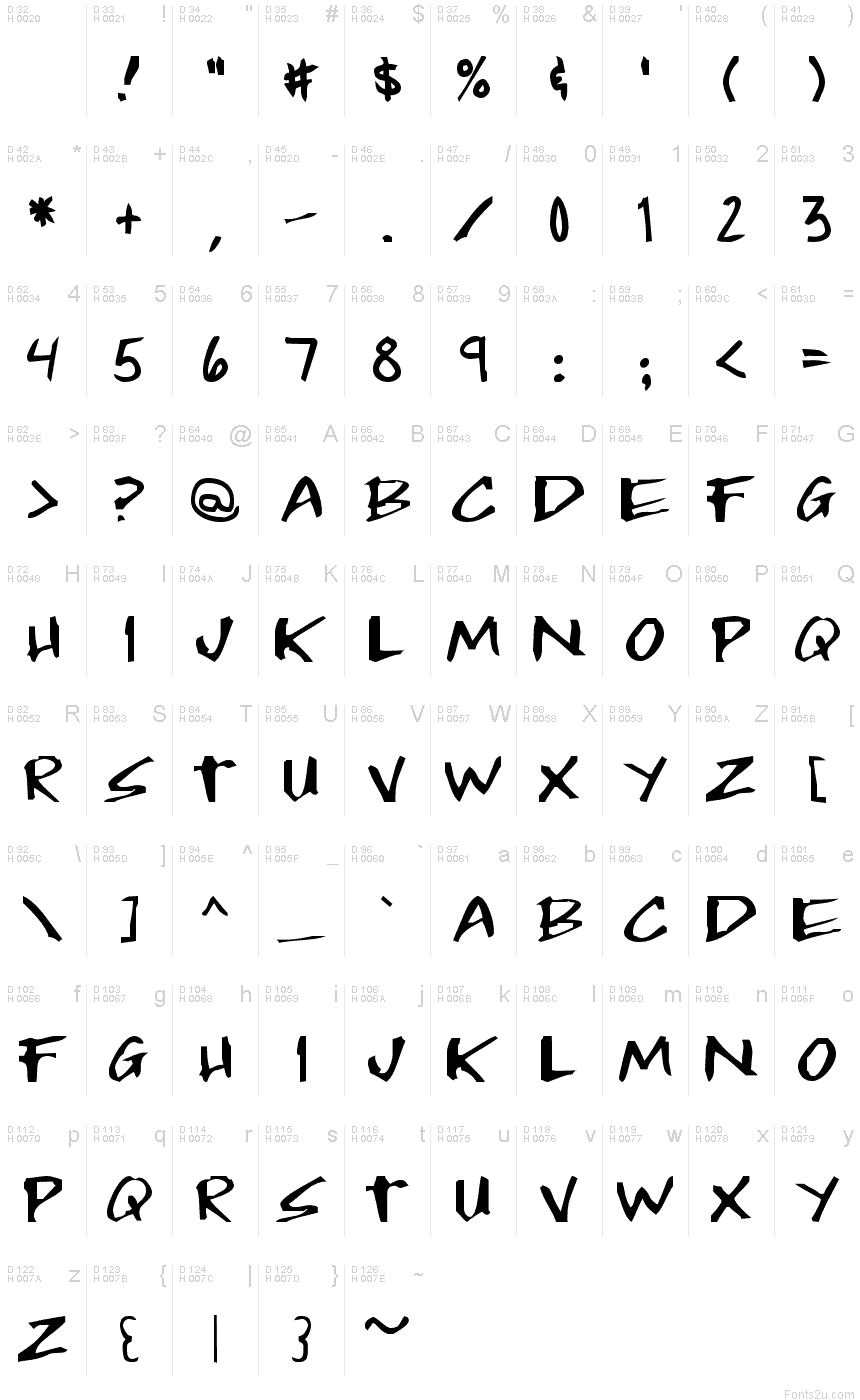
Paradox Now 字体
Paradox Now
Liquid Nite Productions
Andrew Hungerford
Paradox Now 由 Zogoz 设计,是一款免费的变形显示字体,具有扭曲的轮廓和锐利不规则的切口。字母向不同方向倾斜和弯曲,使单词看起来像是一连串破碎的形态,而非普通的文本块。
Paradox Now 字体非常适合需要通过文字来承载整体视觉效果的海报标题、专辑封面、杂志排版、Logo 设计和游戏图形。其破碎的节奏感也适用于活动传单、实验性包装和网页图形设计,在这些场景下,扭曲的图形化标题往往比普通字体更具表现力。